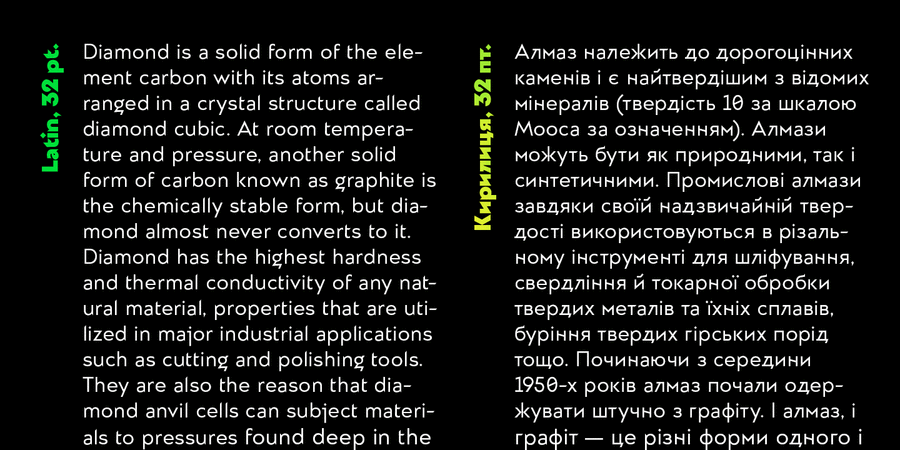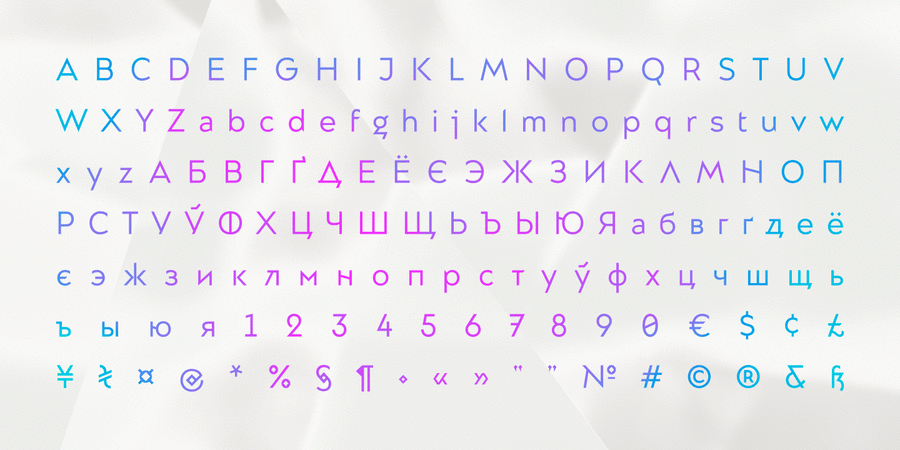
Almaz – це сучасний геометричний гротеск, натхненний українським модернізмом 20-го століття. Він має динамічні форми літер та авангардний характер. Шрифт спроєктований для логотипів, заголовків, книжкових обкладинок, айдентики, також може використовуватись для набору невеликих обсягів тексту. Гарнітура складається з 9 насиченостей (від супертонкого до ультражирного). Шрифт розробили Сергій Макаренко та Кирило Ткачов у 2020 році.
Асоціації з сімейством шрифтів AlmazОсобистість і характер гарнітури:
гострий, трикутний, дзвінкий, чистий, твердий, якісний, модний, точний, холодний, невагомий, легкий, прозорий, худий, скляний, крихкий, ювелірний, кристальний, колючий, різкий, чіткий, сталевий, дивний, архітектурний, міський, оригінальний, самобутній, характерний, дорогий, розкішний, багатий, динамічний, зимовий, крижаний, творчий, незвичайний, сучасний, тонкий, музичний, сміливий, амбітний, екстравагантний, мотивуючий, активний, грайливий, зухвалий, нічний, небезпечний, яскравий, помітний, важкий, щедрий, артистичний, виразний, стійкий, урбаністичний, сильний, потужний, гучний, нав'язливий, осколковий, тусовочний, клубний, двіжняковий, екстремальний, ризикований, епатажний, агресивний, експресивний, жорсткий, радикальний, запальний, чорний, тісний
Інстаграм, ювелір, срібло, скальпель, діамант, ніж, фізика, математика, наука, оптика, дизайн, архітектура, архітектор, прилад, Місто, розкіш, зима, парфуми, люкс, інтер'єр, гра, музика, електроніка, кава, розваги, горілка, алкоголь, кіно, прикраса, фантастика, інструмент, верстат, коктейль, бар, нічний клуб, торгівля, атракціон, шоу, мультфільм, анімація, театр, казино, реклама, клуб, інсектицид, пестицид, каскадер, екстрим, байкер, металіст, концерт, електрогітара, супергерой, рок-н-рол, шолом Гарнітура має ознаки стилів: